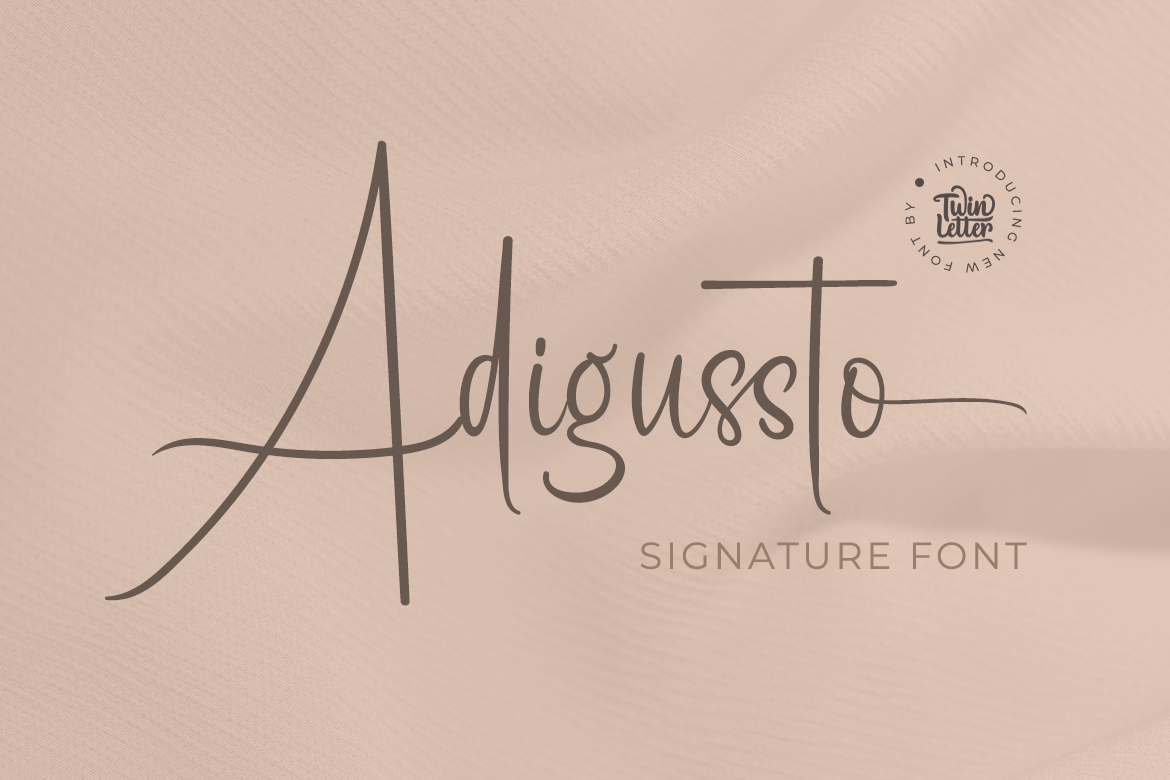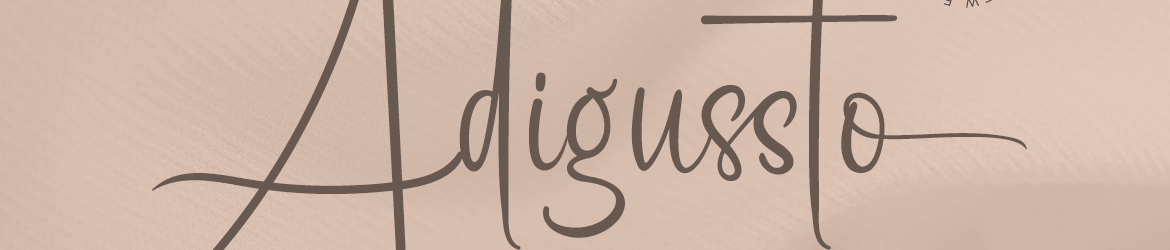
Adigussto Font – Download Grátis
A Adigussto é uma fonte script única e elegante que desfruta de grande popularidade entre criadores de designs, especialmente os artistas digitais do Brasil. Suavemente escrita para um ar pessoalizado, ela se destaca como a escolha perfeita para criar itens especiais como convites de casamento, cartões de agradecimento, cartazes de aniversário e logos. O designer twinletter criou uma fonte que oferece uma ampla gama de caracteres e adoráveis swashes, o que é especialmente útil quando se precisa adaptar seu design à um estilo pessoalizado. O PUA (Positioned Unicode Access) da Adigussto permite que você acceda facilmente a todos os seus caracteres e swashes. Este característica torna a fonte ainda mais versátil para diferentes tipos de projetos, desde cartões de felicitação até logos empresariais. A Adigussto é uma excelente opção para quem busca estilo pessoalizado em sua arte digital. Para o criador de design que procura um toque especial, a Adigussto é perfeita para dar ao seu trabalho aquela pitada única que torna cada projeto único e memorável. Esta fonte vem com swashes adicionais para uma textura mais elaborada, permitindo-lhe criar um design autêntico e moderno que seja tanto sua marca quanto o seu estilo pessoal.